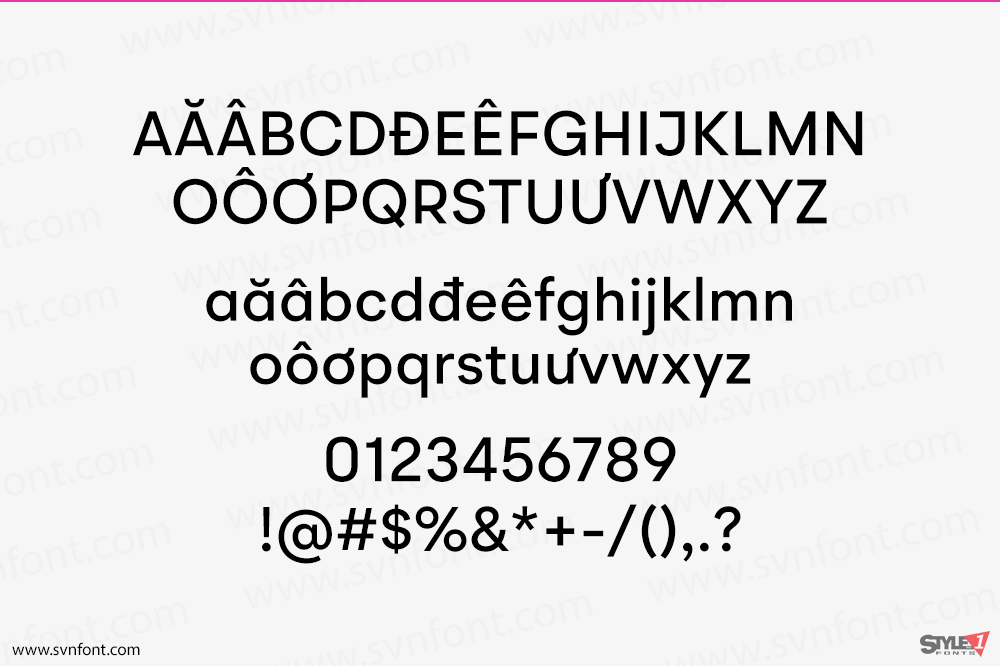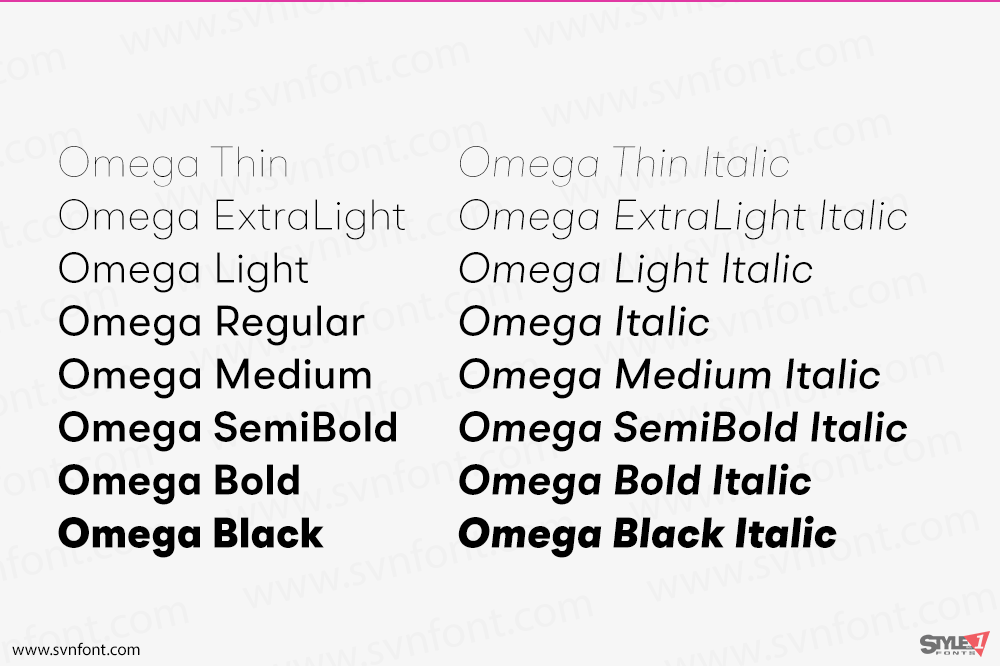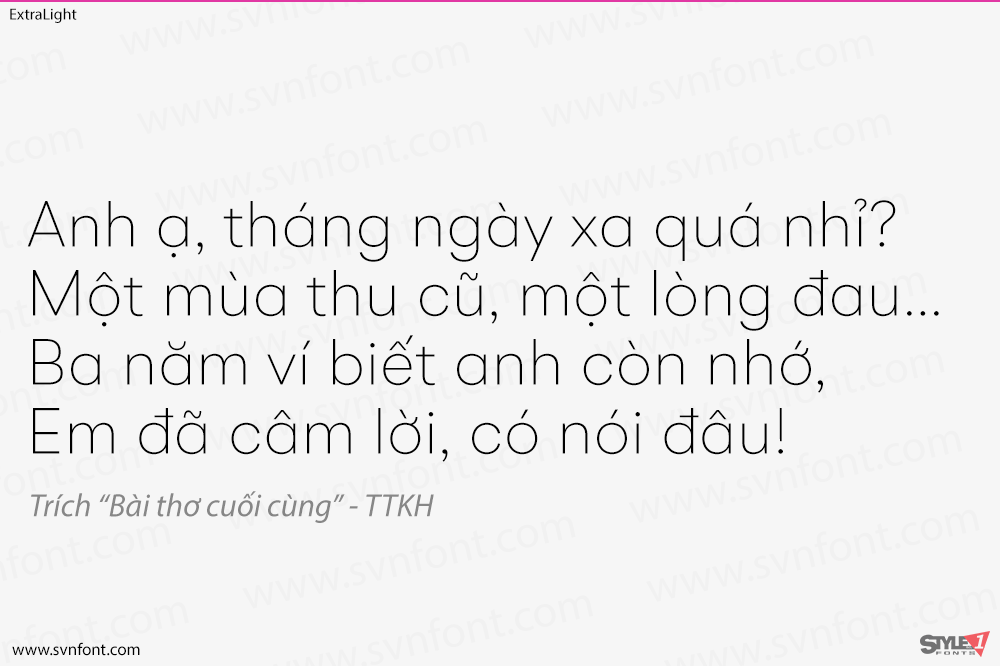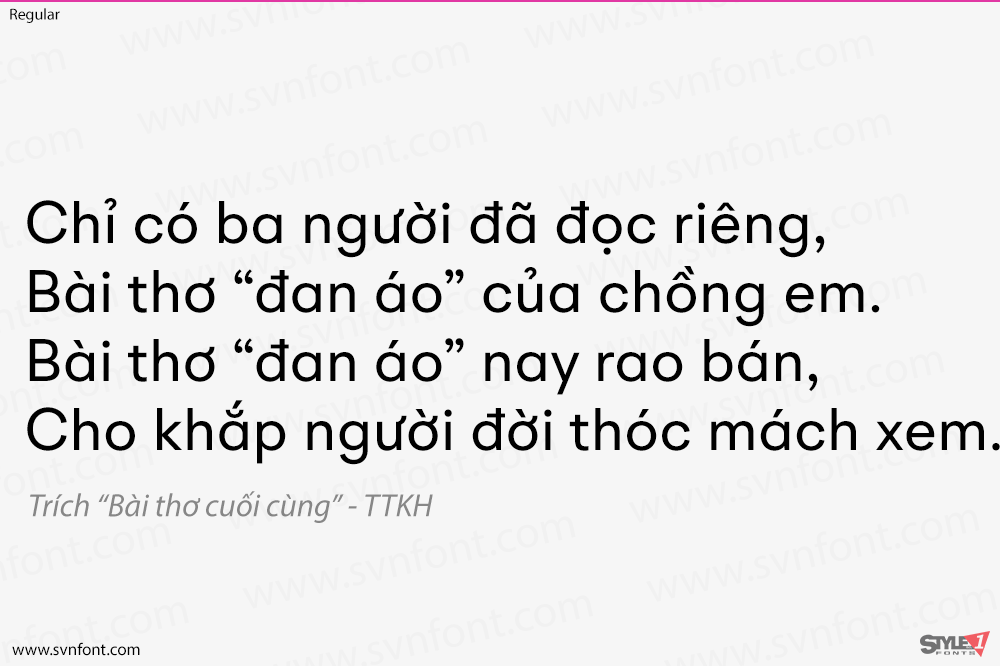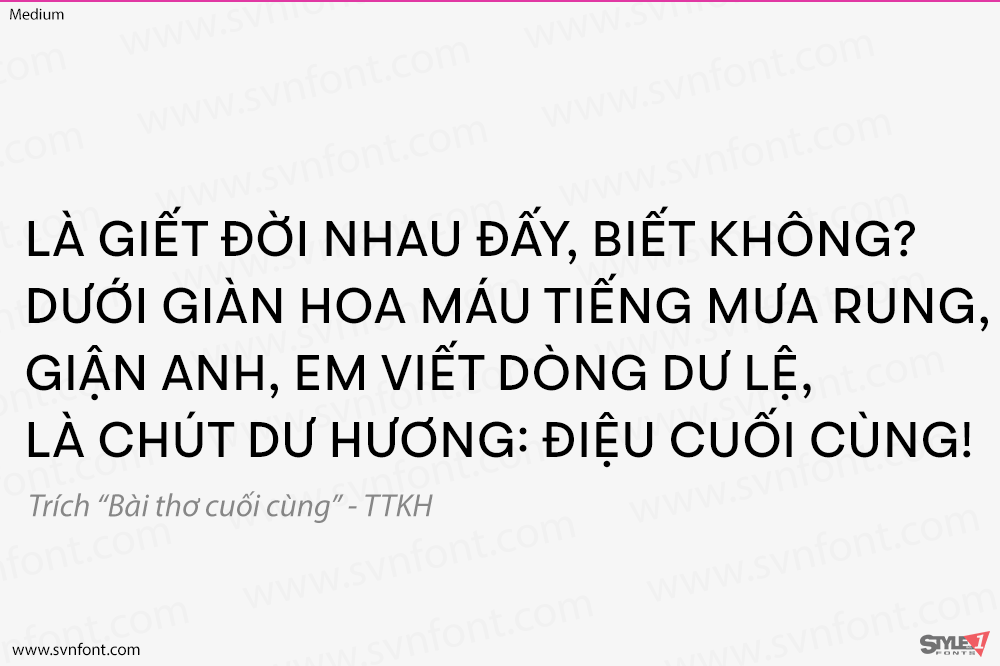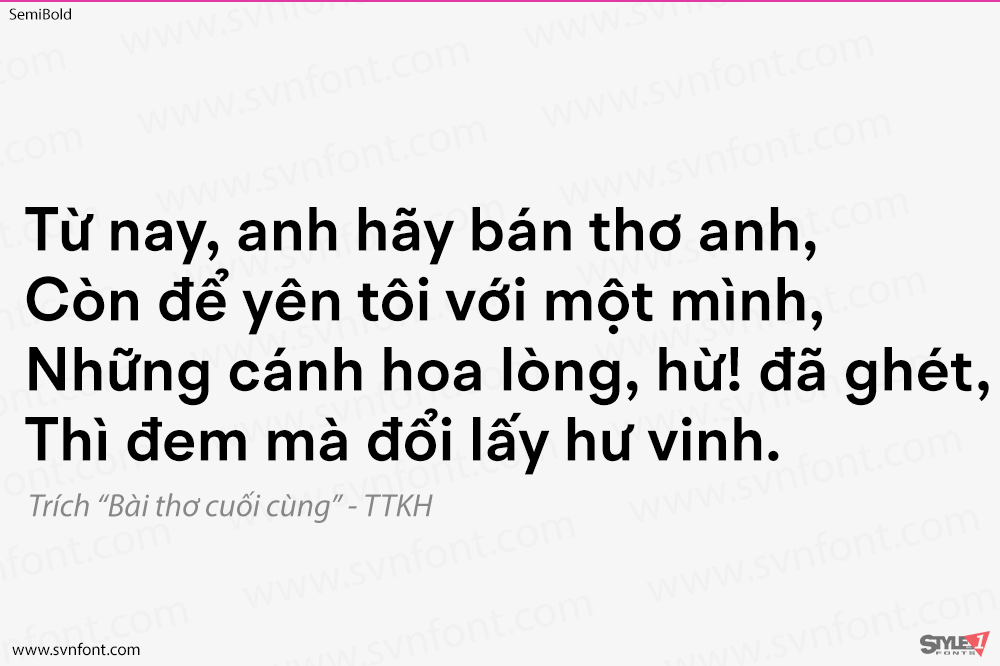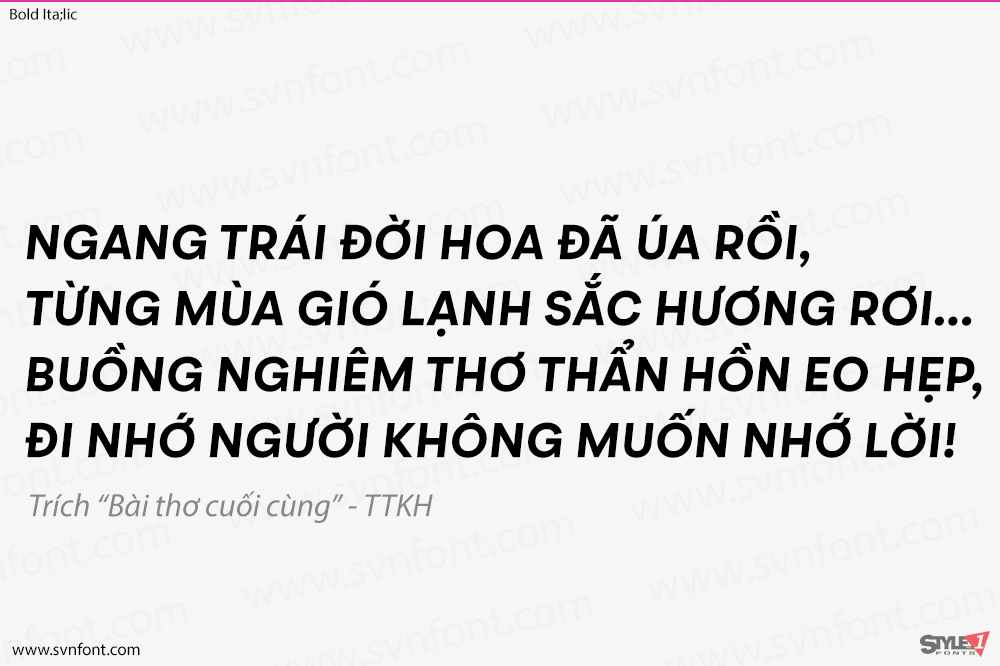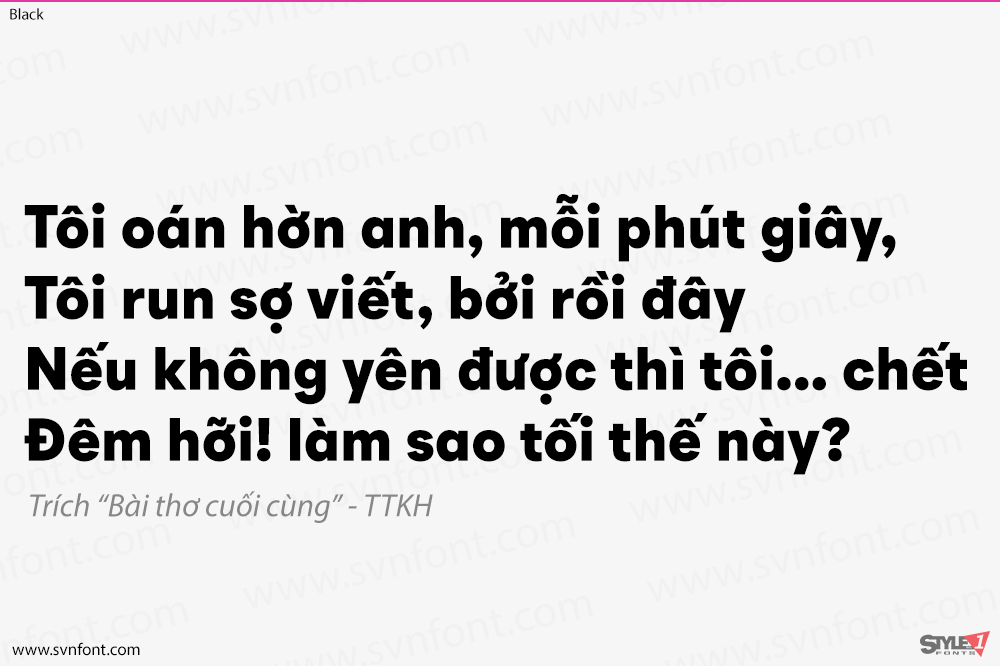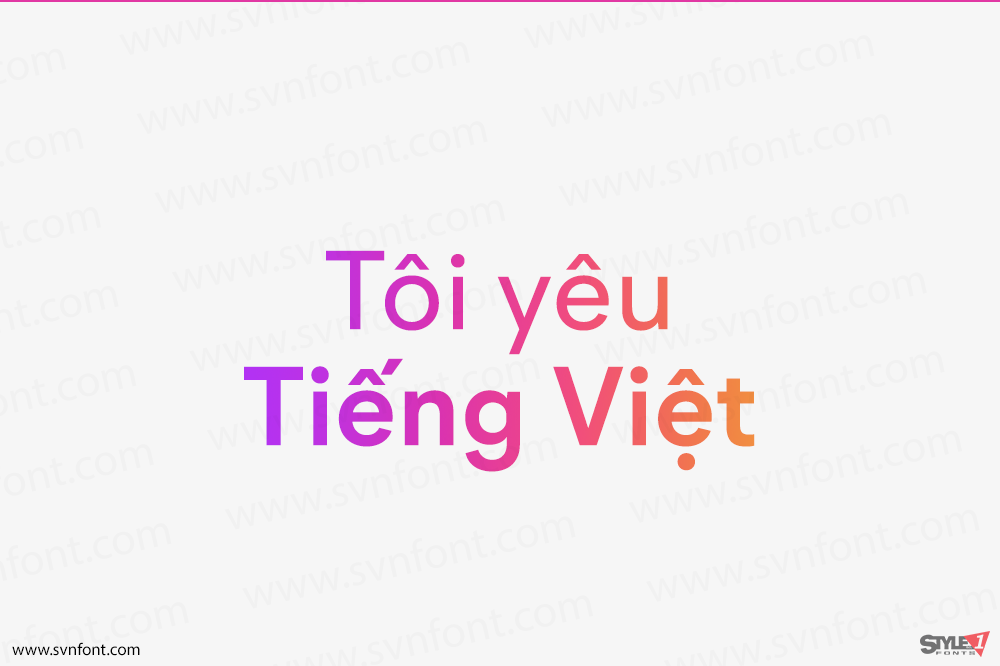
Một họ kiểu chữ hình học có tính ứng dụng cao với 16 kiểu dáng được chế tác tinh xảo. BR Omega là một họ font rõ ràng và hiện đại. Được vẽ và kiểm tra chính xác để truyền tải một thẩm mỹ sạch sẽ và hiện đại. Các đường mở hơi thoáng (apertures) và hình dạng chữ cái cân đối tạo ra một font sans serif có khả năng đọc cao và linh hoạt.
BR Omega cung cấp hỗ trợ kiểu chữ nâng cao với các tính năng như các dạng chữ nhạy cảm với chữ hoa/thường (case sensitive forms), phân số (fractions), số không gạch chéo (slashed zeros) và nhiều bộ chữ số khác nhau (multiple figure sets).
Nhà thiết kế: Christoph York
Nhà phát hành: Brink